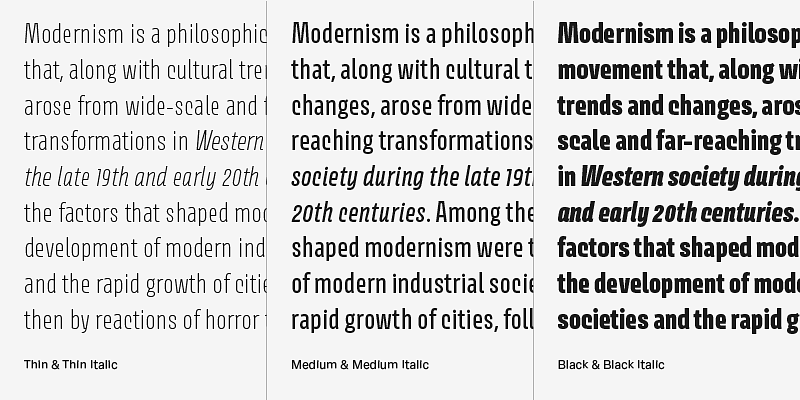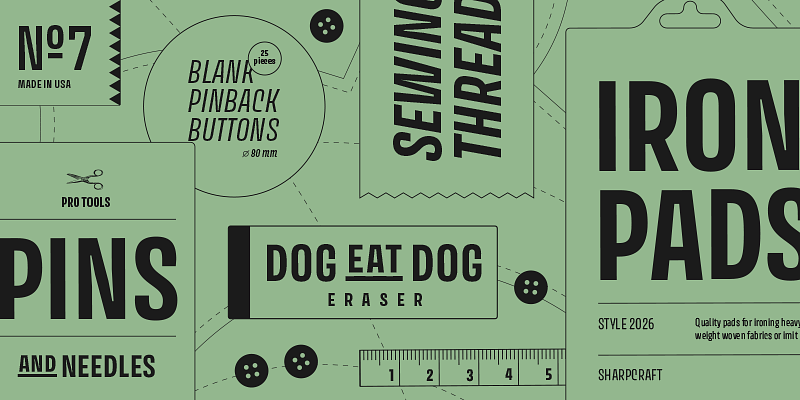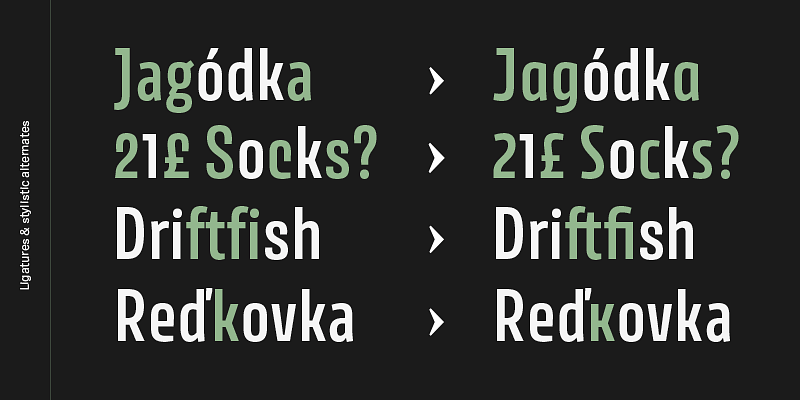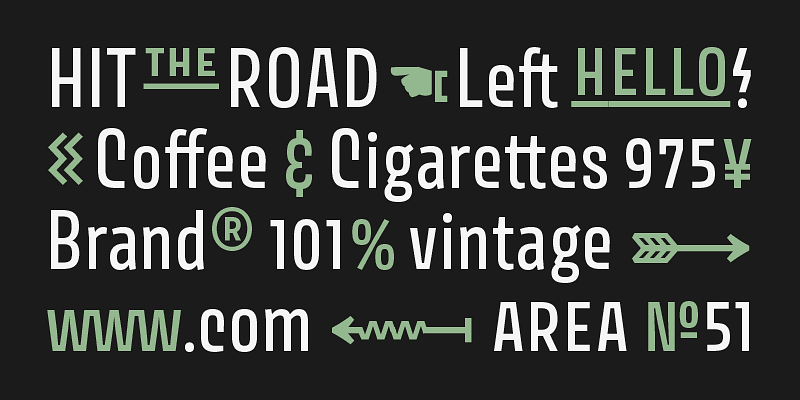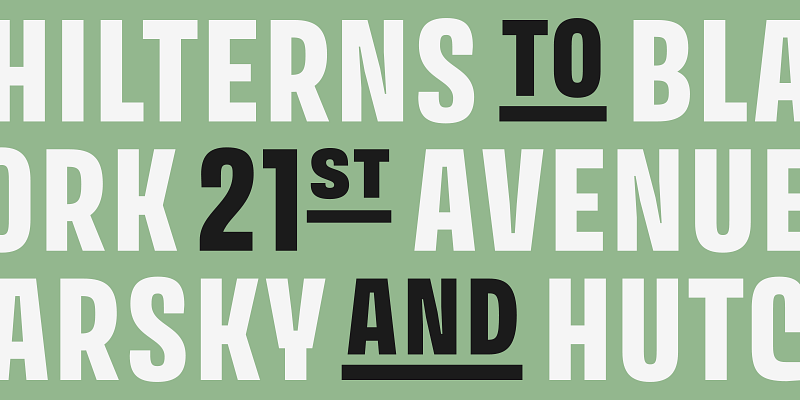
Avory è un sans condensato che sfida le convenzioni. Ispirato al lavoro di lettering del designer ceco Jaroslav Benda, è disponibile in due versioni che funzionano come un outfit diverso.